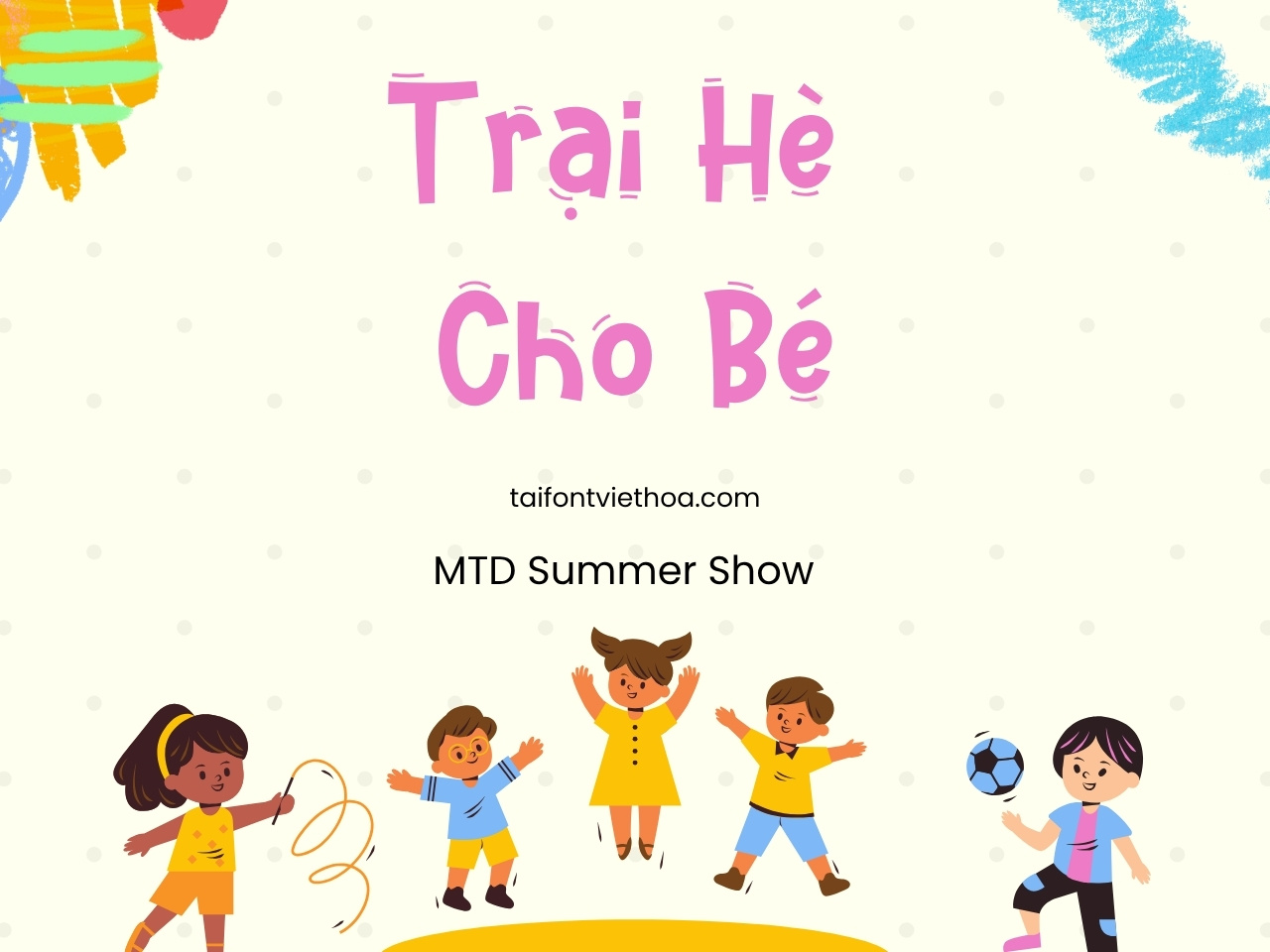
Giới thiệu về font Summer Show
Summer Show là một font viết tay mang phong cách trẻ trung, sôi động và đậm không khí lễ hội mùa hè, được thiết kế bởi Motokiwo Type (MTD) – một studio nổi bật với các bộ font handwriting độc đáo và đầy cảm xúc. Font lấy cảm hứng từ sự ngẫu hứng, vui tươi và năng lượng tích cực, mô phỏng nét viết tay bằng cọ hoặc bút lông tự nhiên. Bản Việt hóa do chính MTD thực hiện, hỗ trợ đầy đủ dấu tiếng Việt và hơn 60 ngôn ngữ khác, giúp font dễ dàng sử dụng trong các thiết kế đa văn hóa và quốc tế.
Đặc điểm thiết kế và ứng dụng của font Summer Show
Summer Show sở hữu cấu trúc chữ ngẫu hứng, không tuân theo tỷ lệ chuẩn, với các đường nét tự do, độ nghiêng nhẹ và các phần chữ kéo dài linh hoạt. Font mang đến cảm giác gần gũi như chữ viết tay thật, phù hợp để tạo ra những tiêu đề sống động và mang cá tính riêng biệt. Hệ thống ligatures đơn giản giúp dòng chữ mạch lạc nhưng không mất đi sự phá cách cần thiết.
Font này rất phù hợp cho các thiết kế như: poster sự kiện, tiêu đề tạp chí trẻ, sản phẩm mùa hè, sticker, bao bì thực phẩm vui nhộn, typography trên áo thun hoặc thiết kế mạng xã hội. Ngành nghề lý tưởng gồm: giải trí, ẩm thực, giáo dục sáng tạo, thời trang tuổi teen, sản phẩm handmade, thiết kế sự kiện và quảng cáo mùa lễ hội.